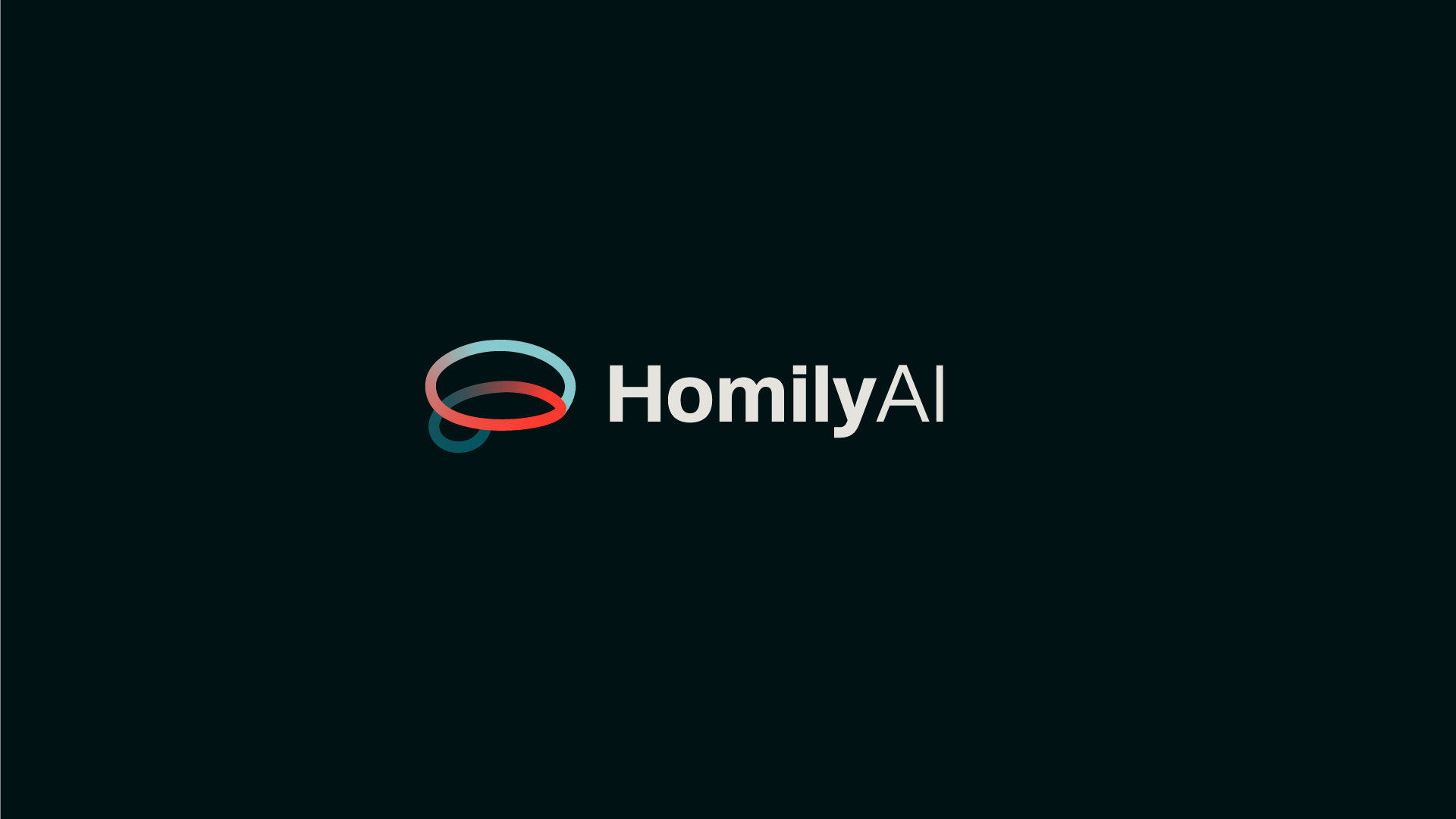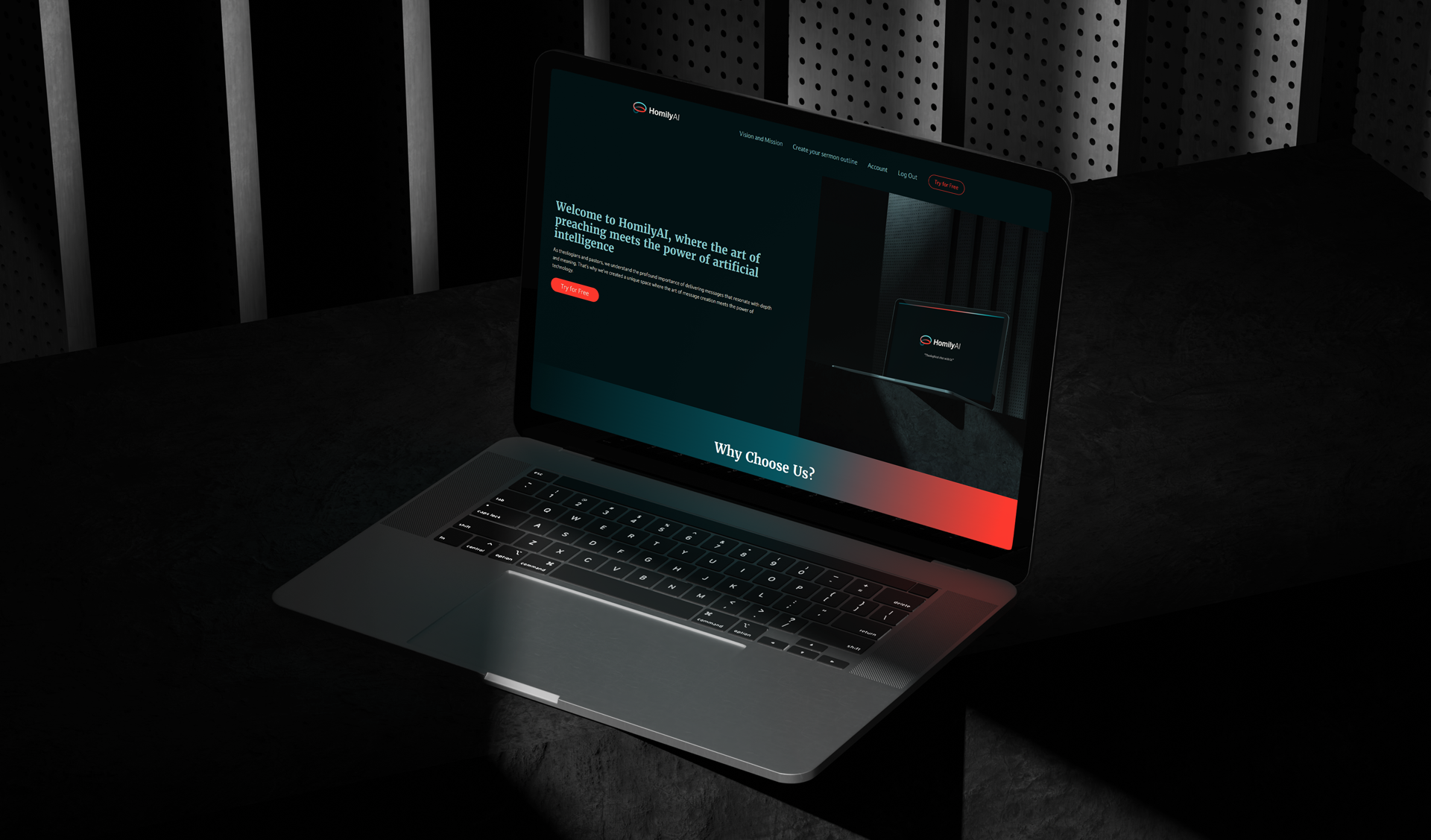
HomilyAI - Meu projeto do curso: Tipografia para construção de marcas valiosas
¡Qué genial David! Es muy difícil conciliar estos conceptos de "antigüedad" con "modernidad", ya que son opuestos. Merriweather logra esto... DarkMode no tiene tanto, pero veo que también funciona dentro de este contexto. ¡Felicidades! (Y perdón por la demora ;)